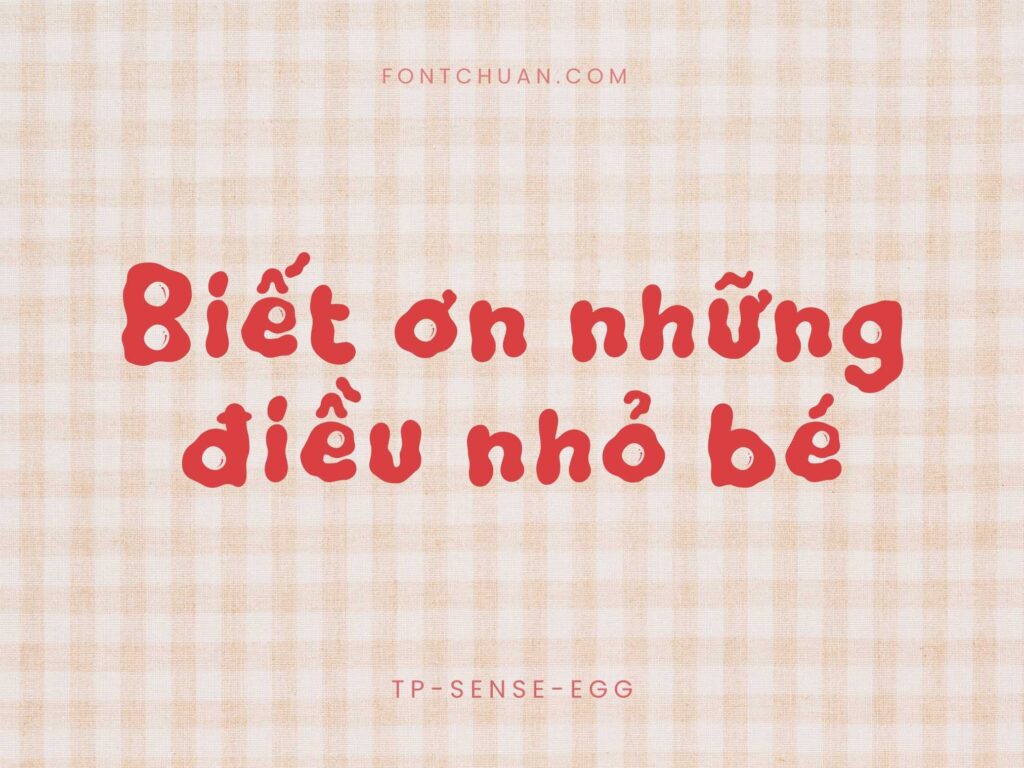
Font TP Sense Egg Trọn Bộ Việt Hóa
Tác giả Font: Attype-Studio
Sense Egg là một Font chữ quảng cáo mang phong cách hiển thị độc đáo, được thiết kế bởi Attype Studio. Font này nổi bật với các ký tự cong vẹo và dáng chữ vui tươi, tạo nên nét thú vị và phá cách cho các dự án thiết kế. Font đã được Việt hóa để hỗ trợ tiếng Việt bởi Tuỳn Pucca, giúp người dùng Việt Nam dễ dàng áp dụng trong các dự án sáng tạo. Đây là một trong những font được sưu tầm và chia sẻ bởi thành viên của Font Chuẩn, nhằm đáp ứng nhu cầu đa dạng trong thiết kế đồ họa và truyền thông.
Đặc điểm thiết kế của Sense Egg bao gồm các nét chữ không đồng đều, tạo cảm giác thủ công và nghệ thuật. Font này phù hợp cho các ứng dụng như thiết kế bìa sách, tiêu đề, poster sự kiện và các dự án sáng tạo khác. Các ngành nghề phù hợp bao gồm quảng cáo, nghệ thuật và thiết kế đồ họa.